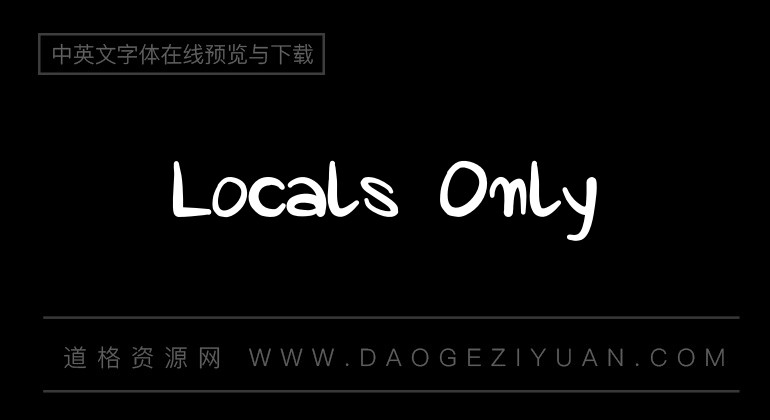
Locals Only是一款手写字体,它具有温暖、舒缓的外观,可以提供出色的设计效果。它的特点是圆润的笔画,比较细腻,可以为您的设计提供温暖的感觉。它的字体大小可以调节,可以满足不同的设计需求。它支持多种字符集,包括英文、拉丁文、希腊文和西里尔文等。它还支持多种字型,如正体、斜体、粗体、黑体等。它可以用于创作各种设计,如海报、广告、卡片、招贴、网页等。内容介绍
Locals Only是一款非常不错的手写艺术字体,具有很好的视觉感,适合于文化类的宣传设计、商业类品牌的广告和产品包装设计以及个性化文字排版等较多场景。